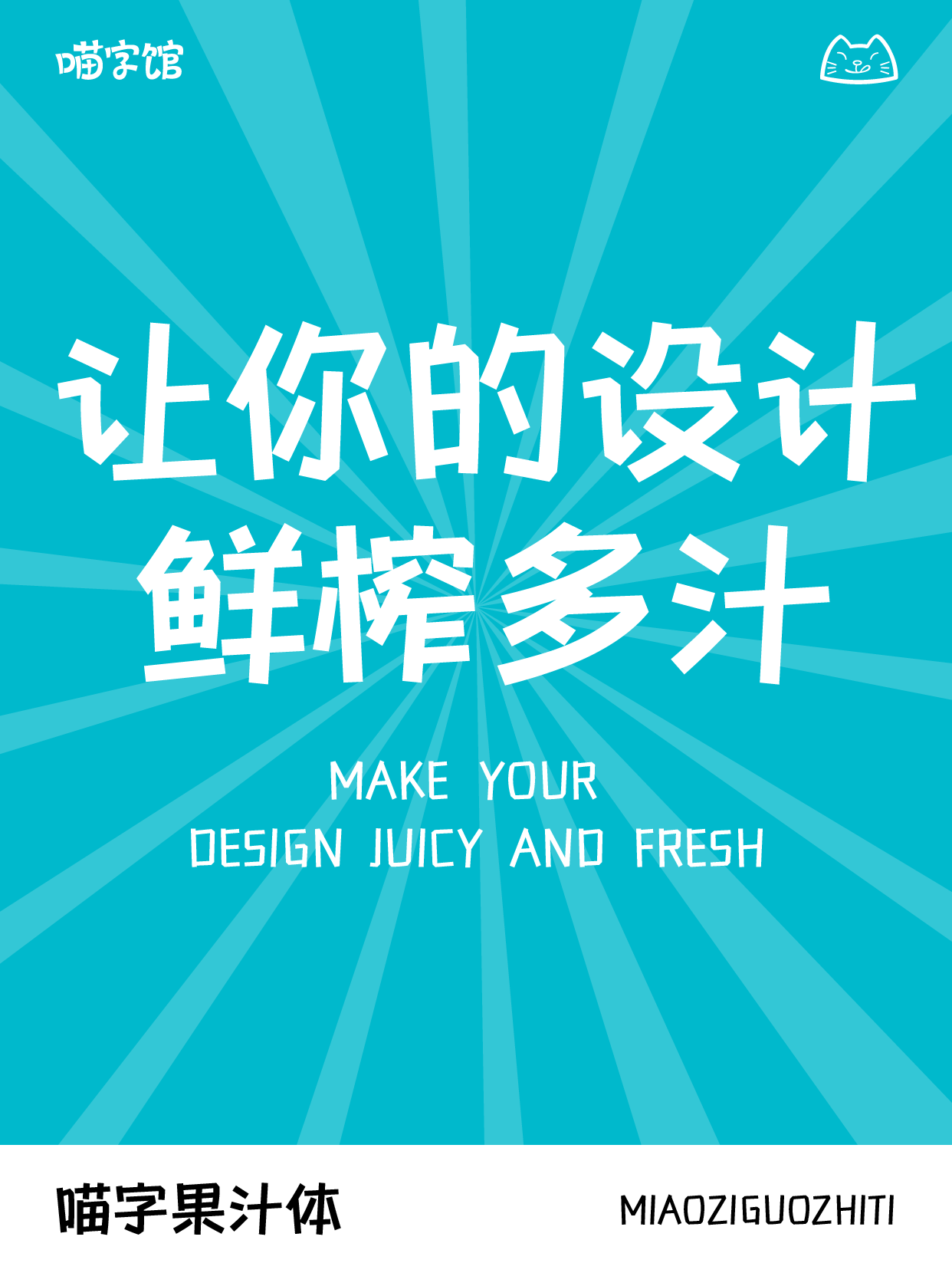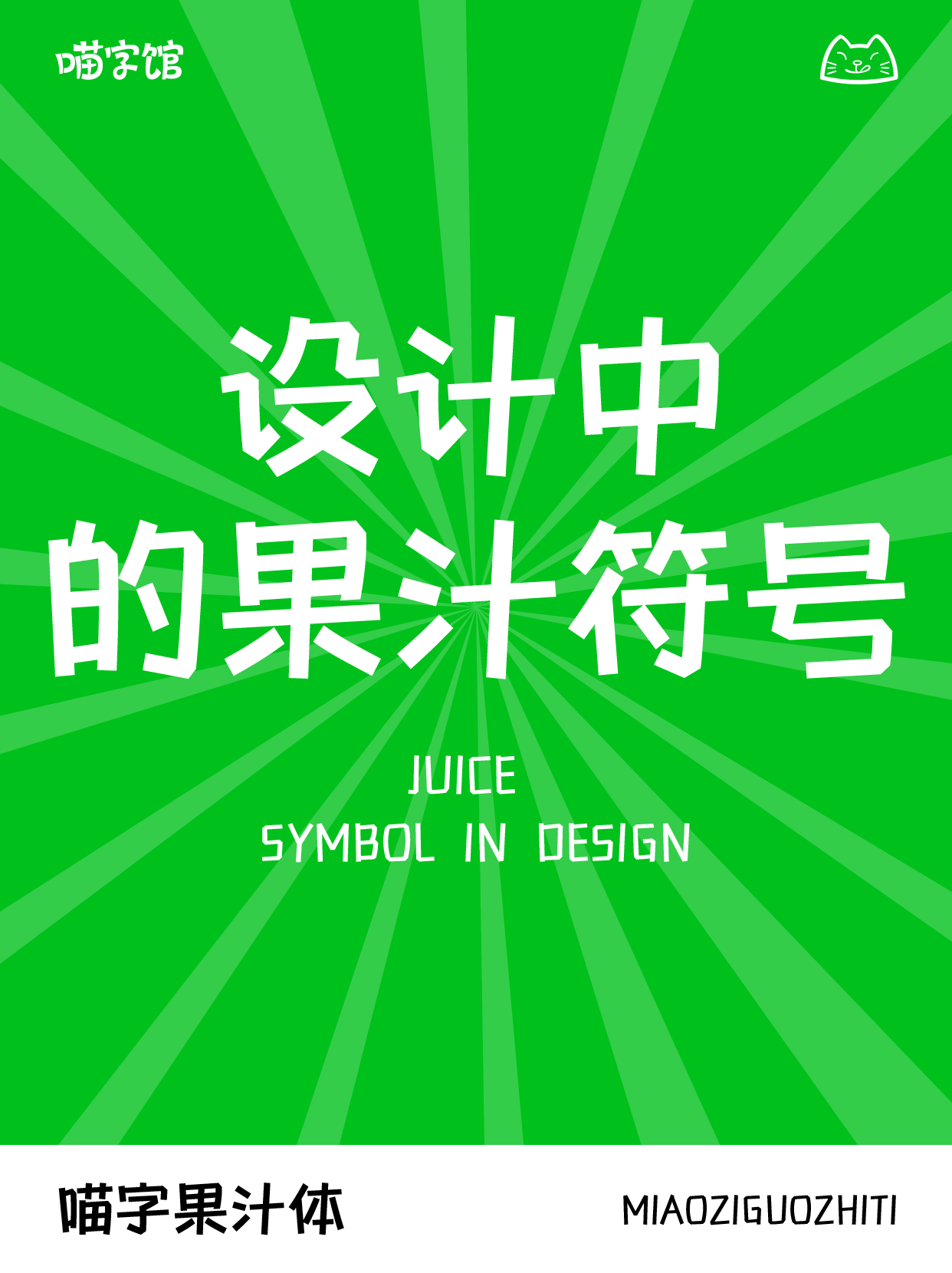
喵字果汁体是一款定位于饮料行业的定制级字库产品。其设计理念源于对饮料文化的深度理解和对消费者需求的精准把握。设计团队发现,在享受饮料的过程中,吸管是一个不可或缺的元素。吸管不仅是连接消费者与饮料的桥梁,更是饮料体验的一部分。因此,设计团队决定从吸管这一元素入手,将其融入到字体的设计中,将吸管的线条感、流畅感和质感融入到字体的笔画中,使得字体看起来既具有现代感,又不失饮料的趣味性。它不仅可以用于产品的包装、广告和宣传资料,还可以用于饮料品牌的官方网站和社交媒体平台。通过喵字果汁体的运用,饮料品牌可以更好地传达自己的品牌理念和产品特色,提升品牌形象和消费者认知度。